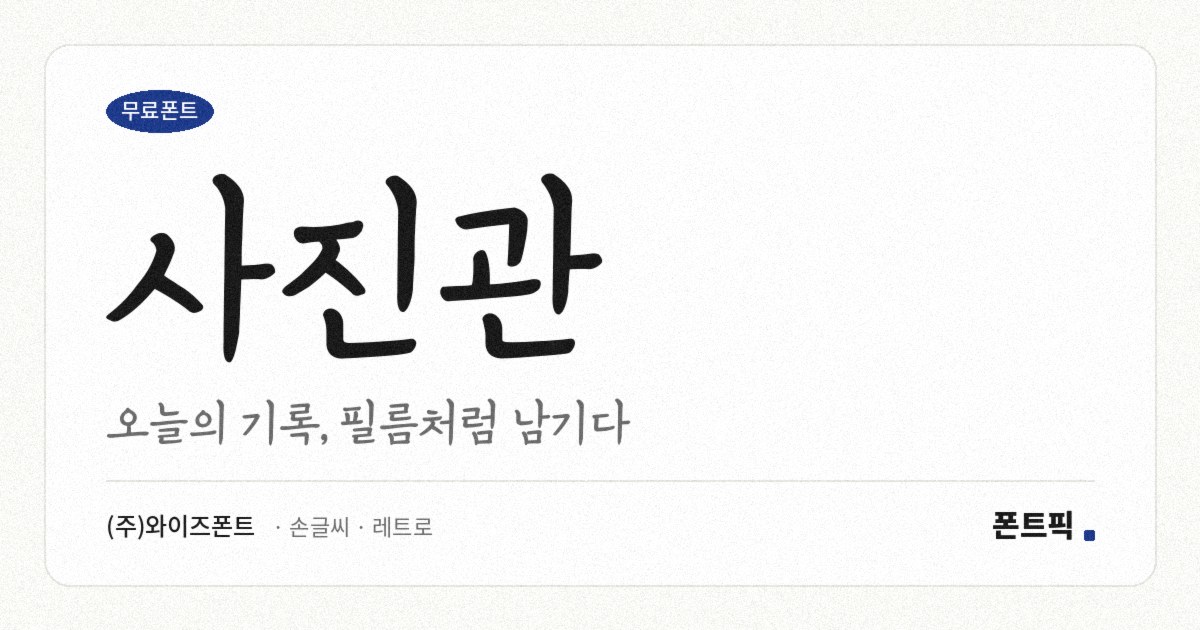
사진관 서체 견본
사진관
TDTDPhotogon
• 굵기1종 Regular
• 글자 수완성형 11,172자
• 분류손글씨 · 레트로
사진관 소개
와이즈폰트의 손글씨 서체로, 장식 없이 필기감만 남긴 것이 특징입니다. 하트나 별 같은 그림이 들어가지 않아 같은 회사의 다른 손글씨체보다 쓰임이 넓습니다.
파일에서 재어 보면 받침 유무에 따른 높이 차가 거의 없어 손글씨인데도 네모틀에 가깝습니다. 낱자는 폭보다 높이가 커서 세로로 선 인상이고, 세로획이 가로획보다 약간 굵어 펜으로 눌러 쓴 느낌이 납니다.
글줄이 가지런하게 떨어지는 손글씨체라 제목뿐 아니라 짧은 본문에도 얹을 수 있습니다. 사진 위에 올리는 캡션이나 앨범 표지의 한 줄처럼, 손글씨의 온기는 필요하지만 산만해지면 곤란한 자리에 맞습니다. 현대 한글 11,172자를 모두 담았고 굵기는 하나입니다.